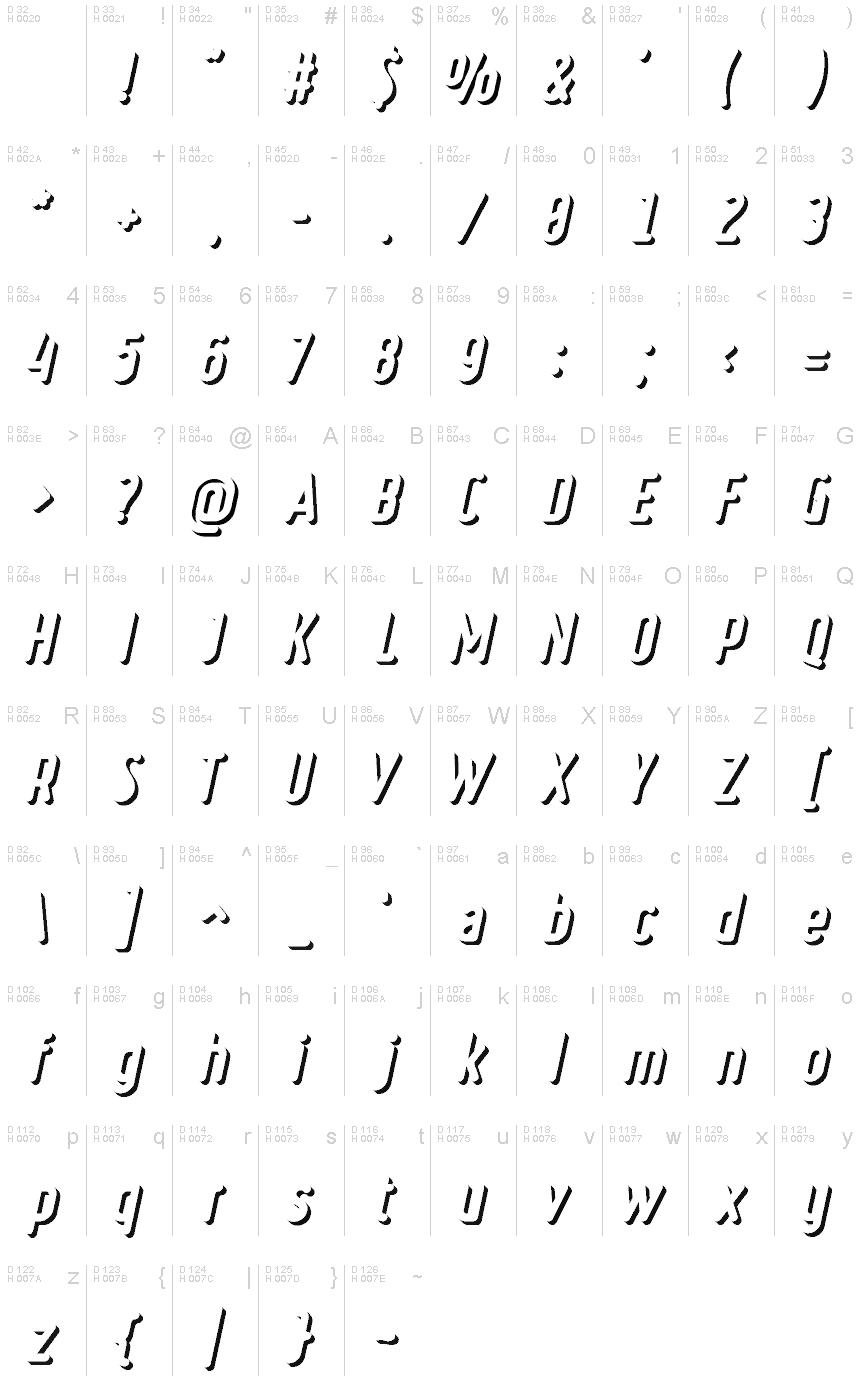
Ruler Volume è un campo giochi di stili tipografici dove l'unico limite è la tua immaginazione. Puoi variare contorni e larghezze spostando i livelli, ma preferisco lasciare spazio alle tue scoperte. Il font offre oltre trenta pesi e stili, ma il mio obiettivo è mantenere tutto semplice e chiaro, senza confusione.
Ruler Volume Outer